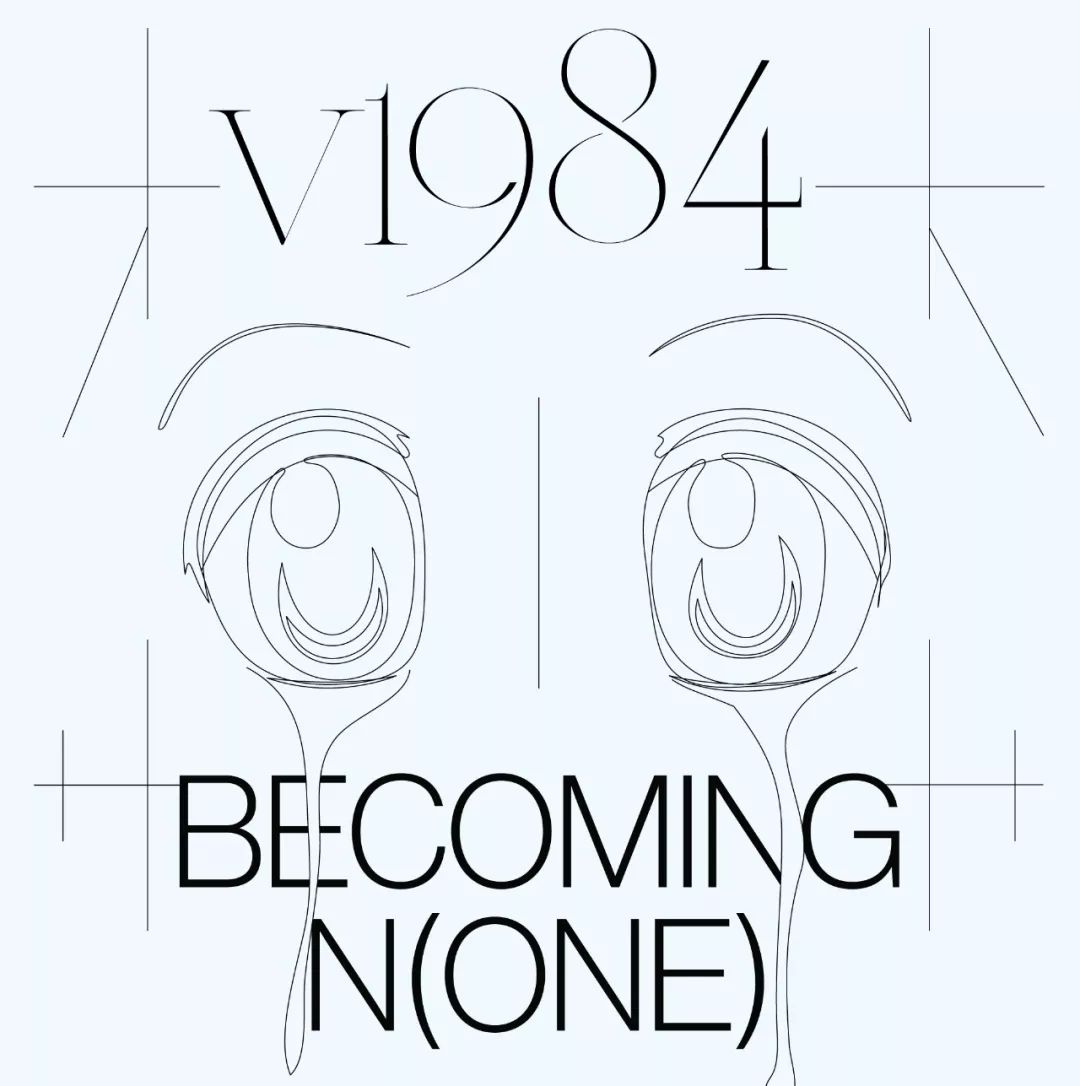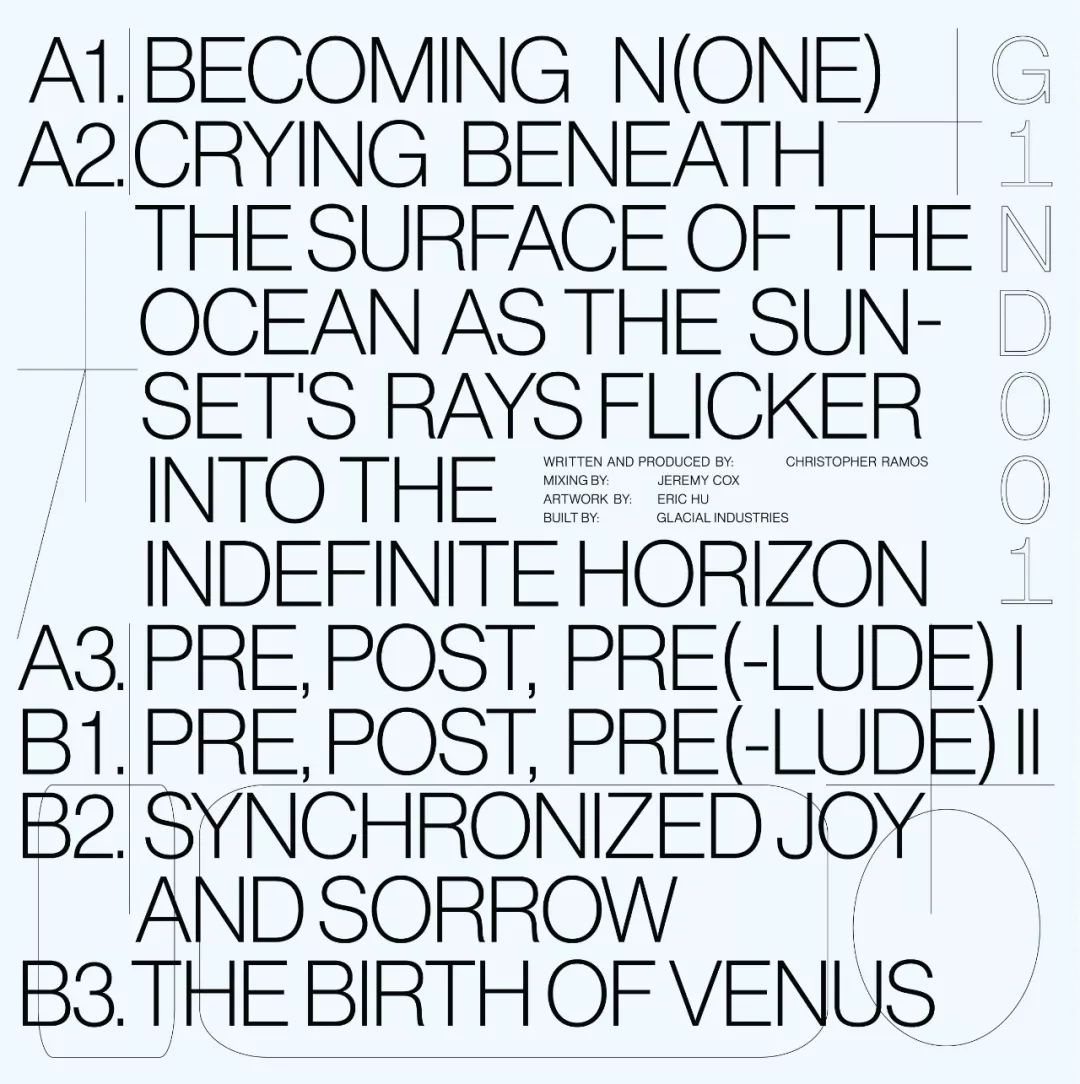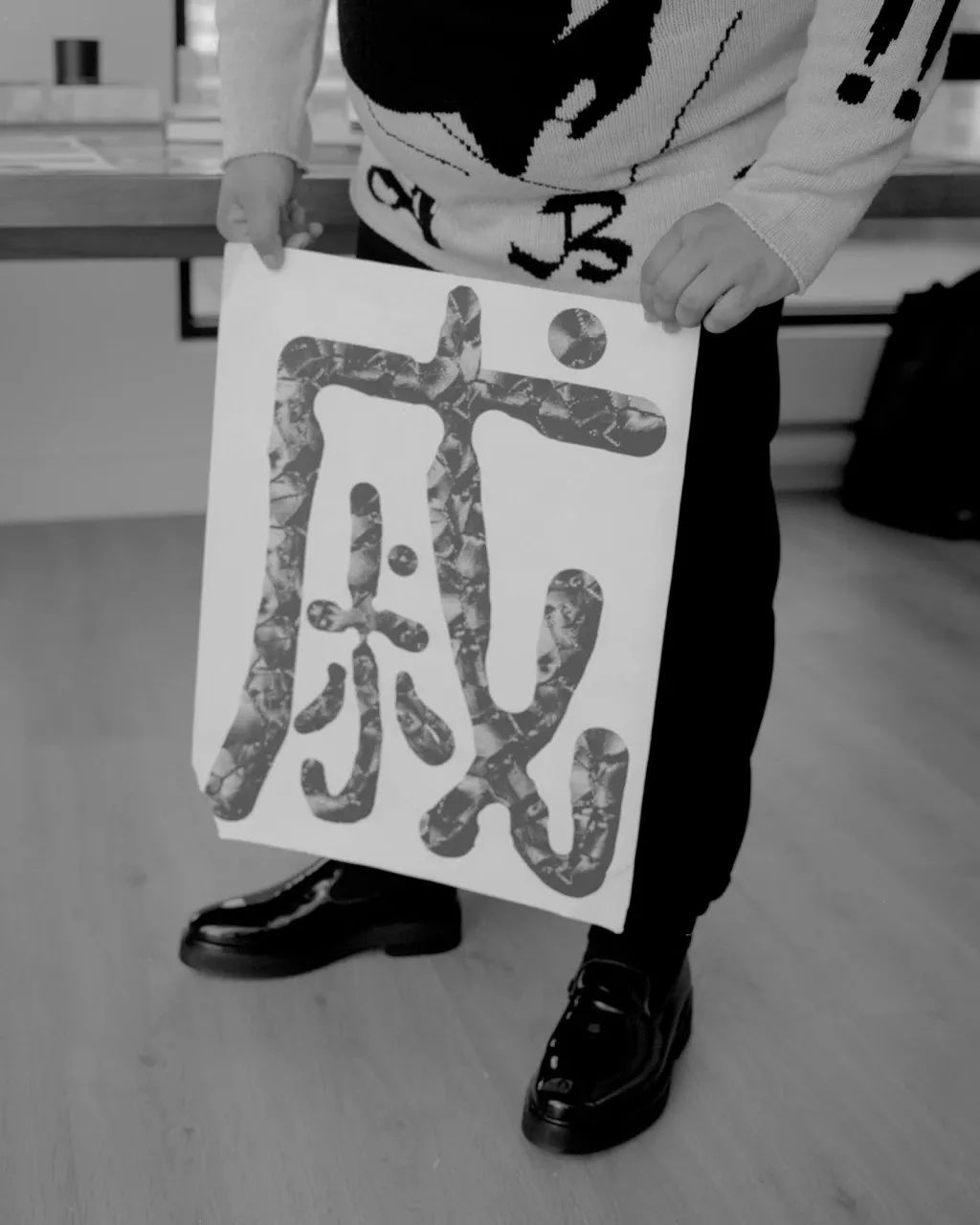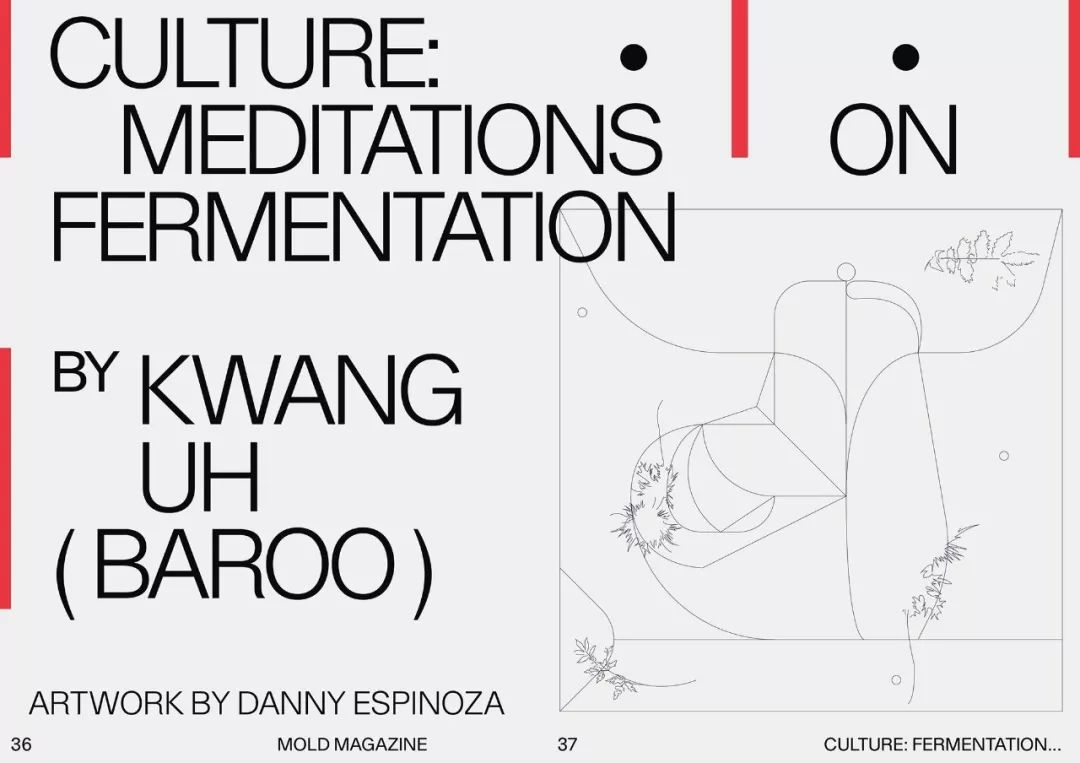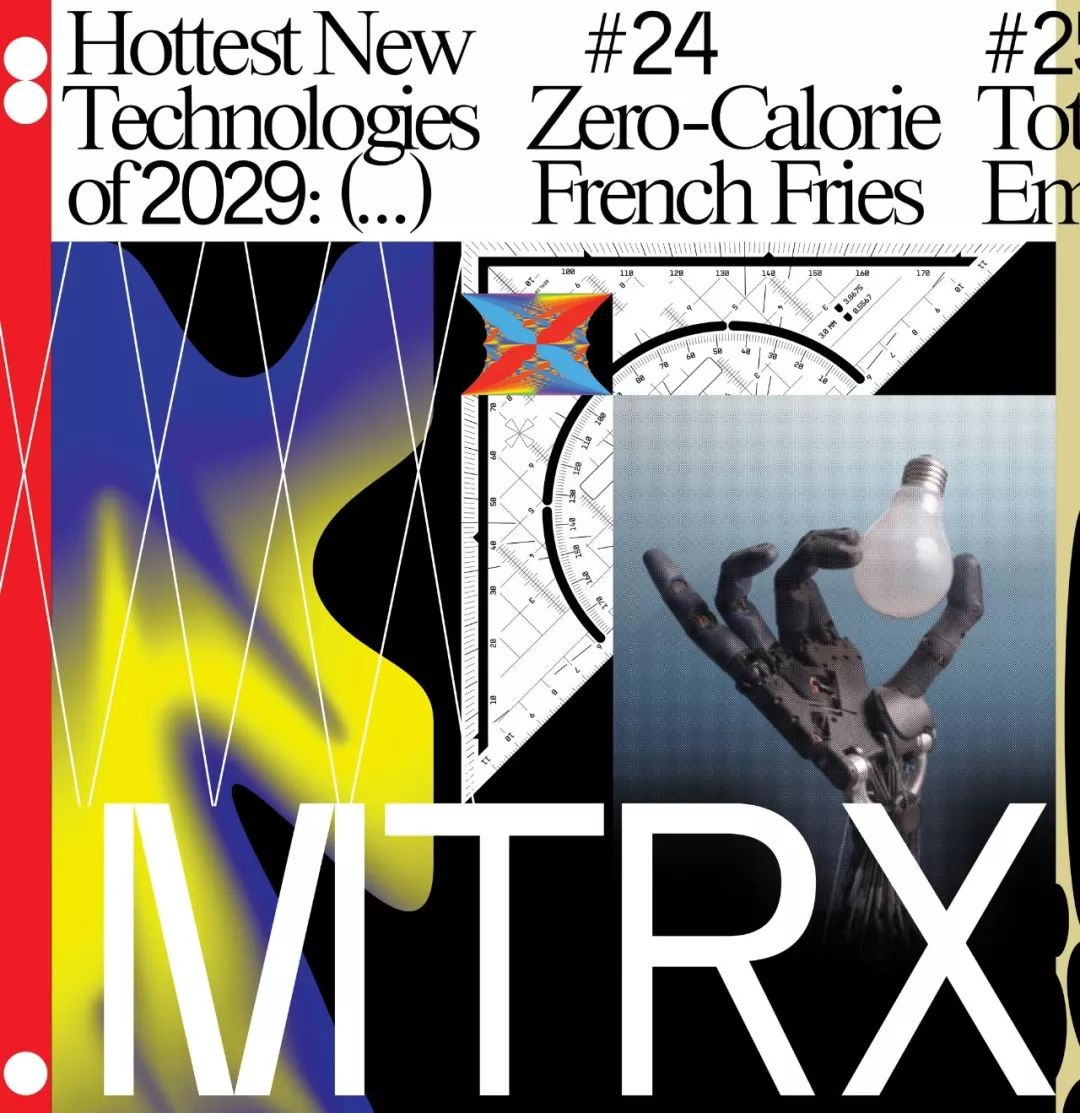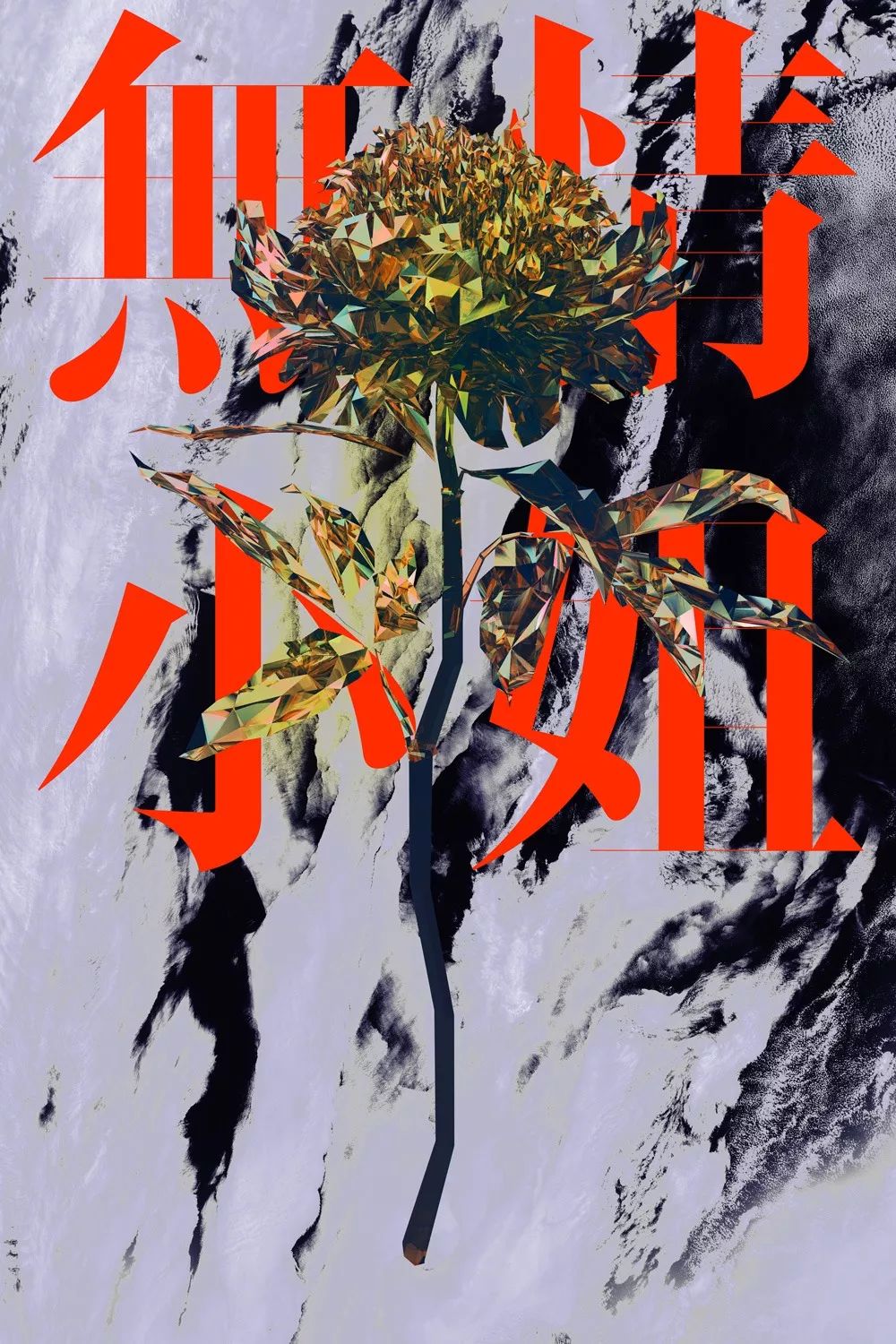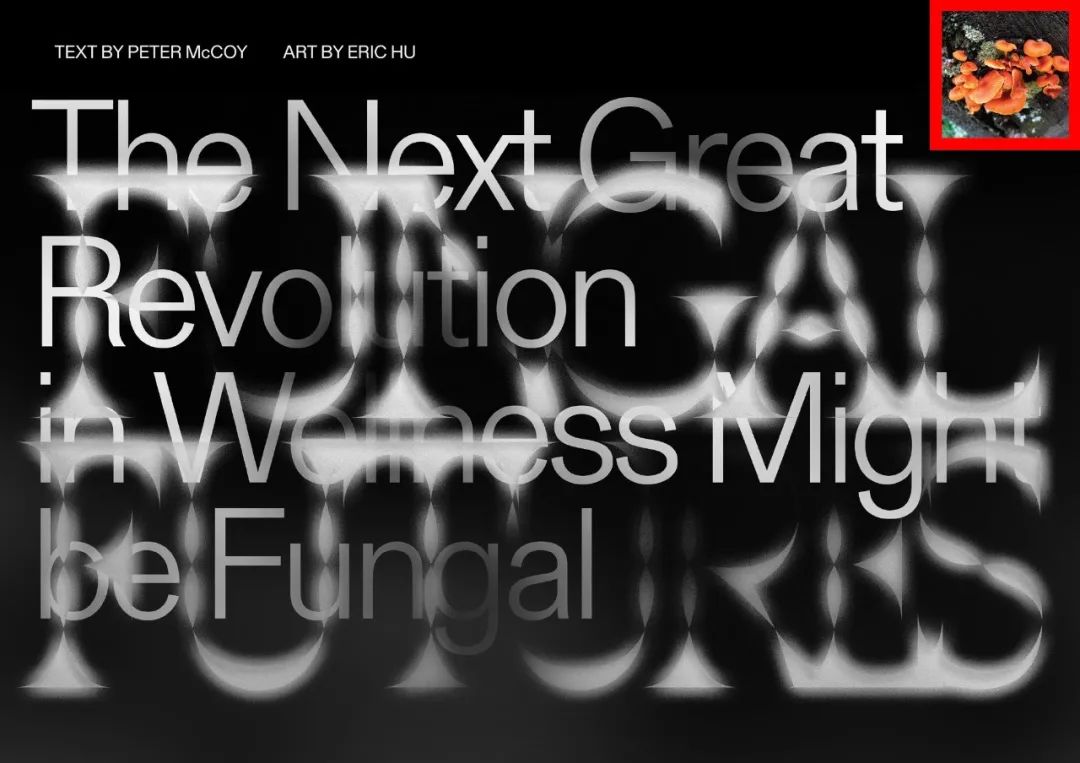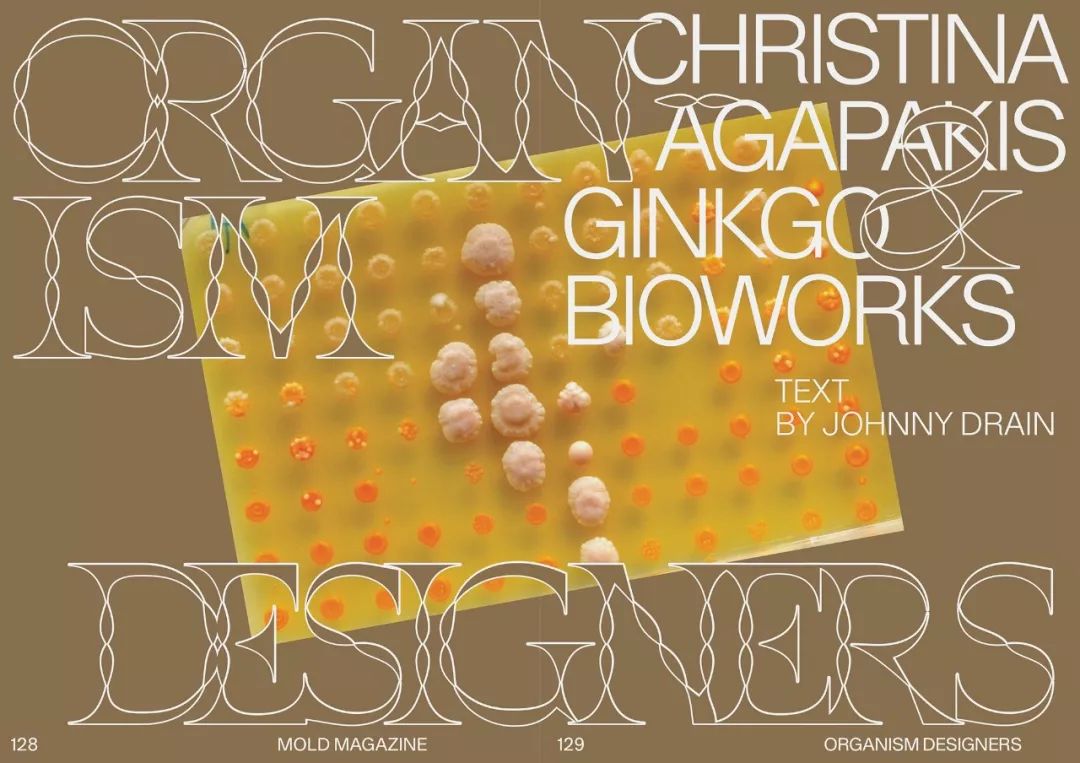
专访Nike全球首个华裔设计总监
Eric Hu
NIKE全球首个华裔设计总监
平面设计是一个令人困惑的职业,因它的抽象,人们无法对它产生直观而明确的理解,因而有损它的声望。只有小部分的行业人士,才能明晰一件作品的微妙之处。同样的,只有少部分的平面设计师,才能获得市场上准确的价值认同。当平面设计师在为某张海报作品或是字体作品进行精雕细琢时;或许在制造产业的流水线上,已经完成了价值千万的产品制造。
我们又要如何去评判、衡量平面设计的价值呢?对于平面设计师来说,如何才能令自己在数字化时代,不那么的迷失自我?与此同时,商业品牌,又应如何恰如其份的,臻选合适的设计师呢?
Δ The Phaidon Archive of Graphic Design
巨匠时代不复返
望着办公室内堆积如山的平面设计书籍,其中不乏在某个时代引领风潮的设计巨匠,如今都与属于它们的时代擦肩而过,沉默地、漫不经心拥挤在书架陕小的空间里,任由尘埃侵蚀。
其中最令人唏嘘的是由 Phaidon 出版社出版的《The Phaidon Archive of Graphic Design》:每位大师的作品只有薄薄的两页纸,分别被归类在不同的类别中,编辑只是对作品进行了臻选和分类,像是一个分类卡片集合,并没有集结成书。或许,这是平面设计的一个小型回顾展吧?
平面设计究竟是一个什么样的职业?它能帮助人们更好地改进现有的生活吗?平面设计死了吗?
从千禧年初,设计天团 theDesignRepublic 的殒落,到近段,声音、体验和装置设计师 Yuri Suzuki以新合伙人身份加入五角设计伦敦办事处(Pentagram London),而曾经的一代设计巨星 Peter Saville,却成了时尚行业的新宠。凡此种种,莫不在提示我们,数字时代中,多元文化的交织及反哺,令整个过程满载惊涛骇浪。来自纽约的华裔设计师Eric Hu,或许是新时代的一位弄潮儿。
Δ Nothing in Common 工作室
在 Nike 工作的音乐人
Eric 经历了纯粹的美式艺术熏陶,出生于美国洛杉矶,2011 年毕业于帕萨迪纳的艺术中心设计学院的艺术学士学位,2013 年获得耶鲁大学的艺术硕士学位。Eric由于工作和生活的原因,经常会往返于美国纽约和加拿大蒙特利尔(SSENSE总部所在地)。同时,他还是艺术音乐团队 Eternal Dragonz 的成员,和来自洛杉矶、悉尼和苏黎世的小伙伴共同创作实验电子音乐(experimental electric music)。
2014 年,Eric 与友人一起创办 Nothing in Common 工作室,2016年加入 SSENSE,担纲设计总监。2018 年 3 月任 Nike 全球设计总监。
钟意高端定制、独立设计品牌的人应该不会放过SSENSE这个海淘平台。伴随着互联网时代开启的全新购物体验,平面设计和艺术指导的融合也变得不那么突兀。品牌的独立ID是离不开设计抑或艺术的全方位支撑的。对于很多独立品牌设计师来说,SSENSE集合式的存在引领了时尚和艺术的二次曝光和再次创造(Our redesign is the result of a collective SSENSE effort)。
作为 SSENSE 的设计总监,Eric Hu 在平面设计领域的作品,涵盖了时尚、音乐、建筑、科技等多个方面,以极致的手法和细微的专注,打破了视觉艺术层面和产品功能层面之间存在的隔阂。
Δ 穿着 Prada + Kiko Kostadinov,Eric Hu 对时尚见解独到
Δ Eric Hu 与他的作品千字文
各种跨界尝试,为Eric的艺术创作带来了天马行空的思路。对固有品牌的集合与再造是SSENSE一直在追求的,时尚买手在这个时代可以通过互联网平台轻易地实现。
如何从上百个设计师的作品中找到共鸣与共通?如何在杂乱无序的物件中找到属于SSENSE独有的颜色?如何把Acne Studio、Balenciaga、Chloé、Dior、Essentials等等这些看似违和不相干的品牌和谐地摆放在同一个视觉维度?来自Eric Hu的回应——
Δ 为 SSENSE 设计对名片Δ Eric Hu 为杂志艺术指导的摄影作品
Δ Eric Hu 为 V1984 设计的唱片封套(正面)
Δ Eric Hu 为 V1984 设计的唱片封套(背面)
当 Eric 遇上 SSENSE
在Eric看来,真实性这个词语无论是在艺术层面、还是产品层面,都被过度滥用了。真正意义上的绝对真实,已经脱离了艺术追求的层面。设计的力量,在于可以以假乱真。这里的“假”是视觉影像带来的错觉,与绝对的虚假或者错误无关。
在娱乐至死的受众需求推动下,SSENSE逐渐有了一点青少年的样子。Eric 提到,SSENSE 从2003年成立至今,并不是在一路试图找寻自己的声音,而是在找寻一种更好的方式去诠释这个时代赋予少年成长应有的态度。改变和调整,必然带来内心的不安与悸动。对于品牌重塑(reband)来说,不断更新的设计思维更有益于保持品牌生长力。
虽然在洛杉矶长大,但 Eric 一开始对奢侈品牌并不感兴趣。但在大二的时候,Eric 第一次发现了 SSENSE,遇见了类似 Comme Des Garçons, Gareth Pugh, Rick Owens 等等全新的品牌,颠覆自己对时尚的定义和偏见,对这个行业突发性地产生了巨大的兴趣,也成就了自己在平面设计师和艺术指导交叉道路上的碰撞与火花。
Δ 他和 SCOTT LANGER 为 THE AVERY REVIEW 做的网站元素
Δ 《MOLD MAGAZINE》杂志设计的跨页
Δ 他为《无情小姐》——探讨选美比赛之艺术展——的海报
成为时尚界的局外人,至关重要。
把完全不相关的上百种品牌单品汇聚在同一个时尚平台,Eric采用了平面设计最常用的排版设计,来指导艺术时尚的呈现,赋予SSENSE全新的身份特性(identity)。Eric选择用物品最原生的状态,组合出一种更为和谐的视觉呈现,优雅而精致( elegant and refined)。
我们想要设计出一种非常无害但略显无趣的排版设置。
Eric选择用最单一的排版设置来突出产品原有的气质,比如Arial系统字体的标题设计,Times New Roman标准字体的段落文字;但是一些局部的创意设计又会给予整个页面活力,比如数字“8”是颠倒的,字母“R”是块状的,字母“S”是倾斜的。单一无趣的排版给人熟悉感,细节创意的设计给人无限想象。
时尚常常痴迷于构建幻想世界。基于现代社会的视觉思维模式,图像能够给予的真实感在逐步被削弱。Eric摒弃了花哨的设计元素,选择更无趣的文档编排,来实现幻想世界。创造完全无意义时尚,已经脱离了当下的主流追求。现实,才是最终的艺术总监(Reality is the ultimate art director)。
不刻意去拥抱真实才是时尚追求最真实的表达。无论对世界,对生活,还是对时尚,对艺术,我们始终鼓励大家保持质疑,但切记犬儒(to encourage skepticism, but not cynicism)。
Δ MATTER OVER MATRIX, 他为 Addidas 的 “FUTURE CAPSULE” 展览而设计
Δ 客户:《FAT MAGAZINE》杂志
Eric Hu x 《Mold》 杂志
Δ 为杂志创刊号设计的封面 & 字体
杂志内页设计
Eric Hu x 千文字
来自于中国古代的《千字文》,是南朝梁的周兴嗣所作的一首长篇韵文。它是由一千个不重复的汉字组成的文章。Eric Hu 运用滑鼠字型插画画出这不重复的一千个中文字,富有韵律感的趣味。
你即世界
Eric 的成长及教育经历,令Eric捕获了一些精湛的视角。他擅长在正式的,普通的文本中,置入一些矛盾的、荒诞的图像,亦或是将他个人记忆中的物体再现,构建一个奇妙的记忆世界,却与现实千丝万缕。
在Eric 的作品中,字体、插图、图像,互相混合(Mix), 构建了一个奇异的混合感官世界。从某个层面来说,这印证了,“你即世界”的哲学预言。一场自我革命。